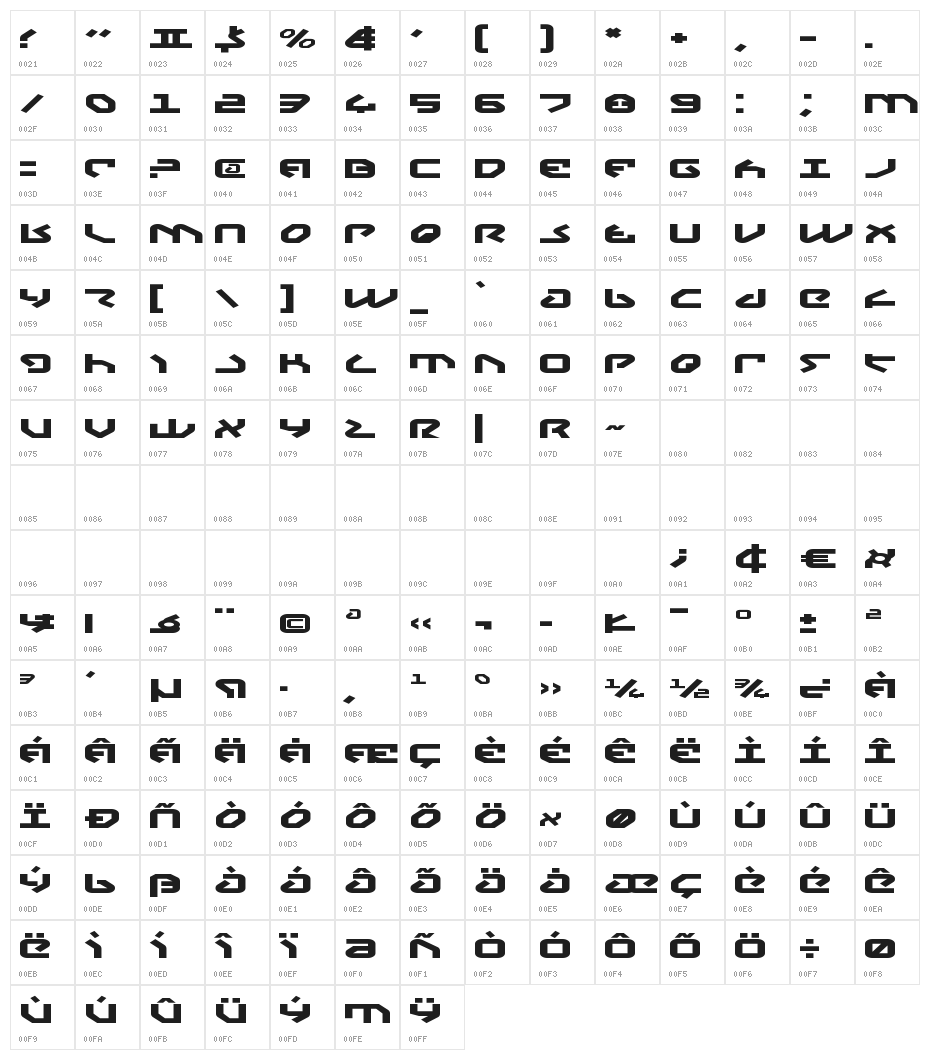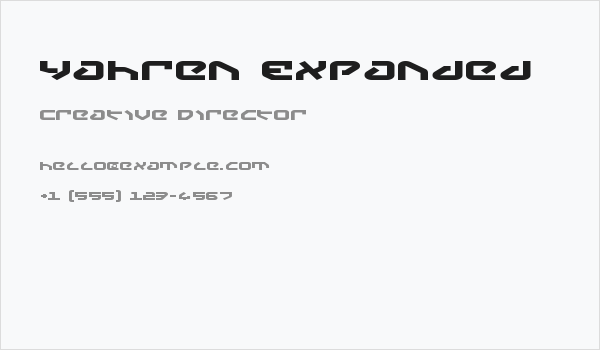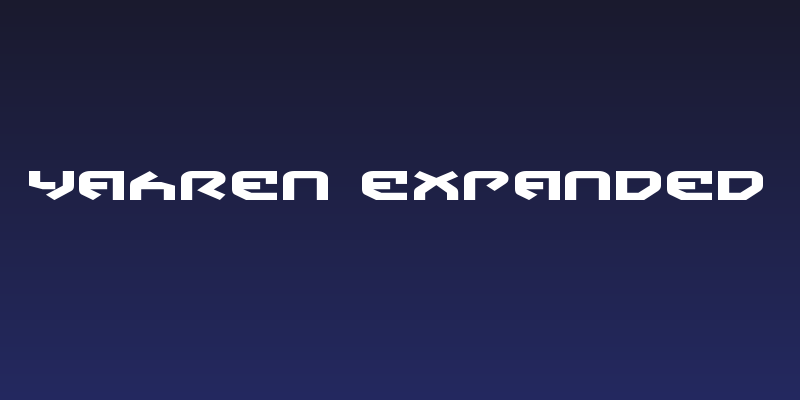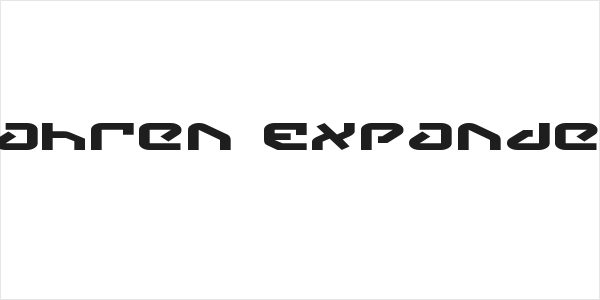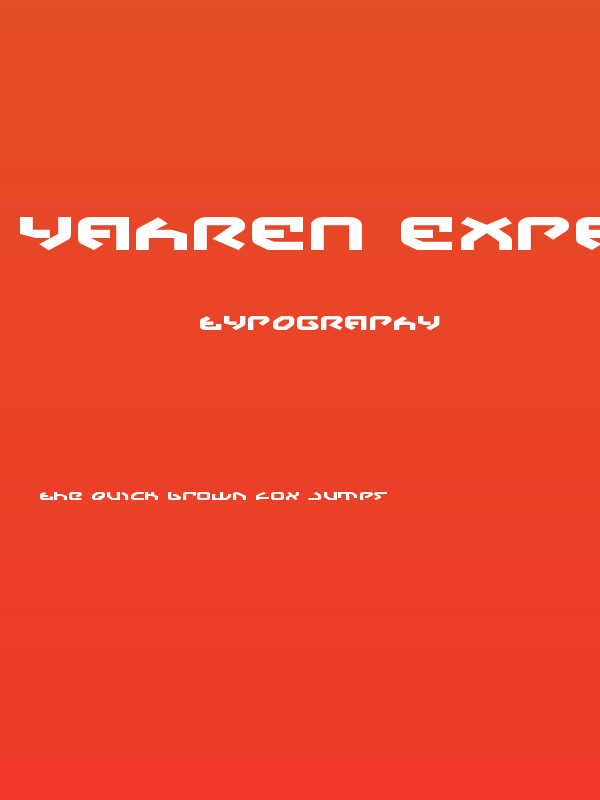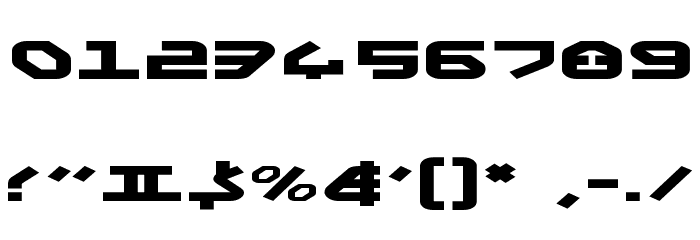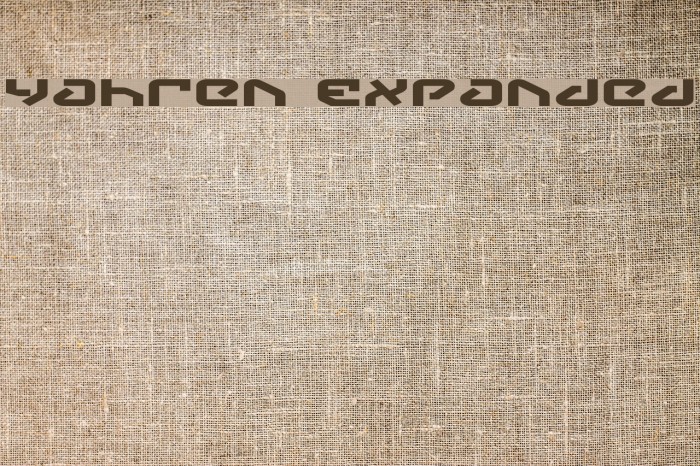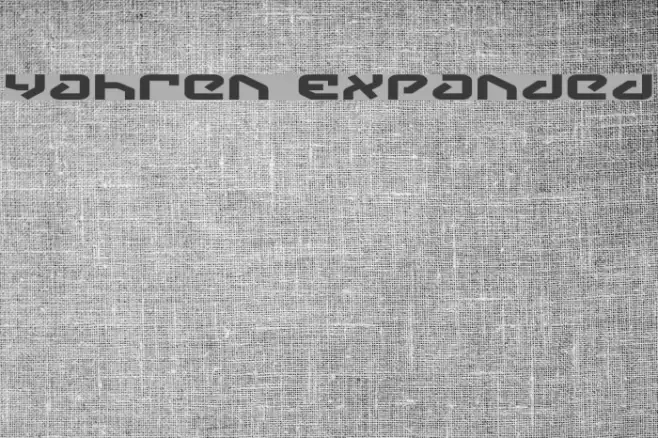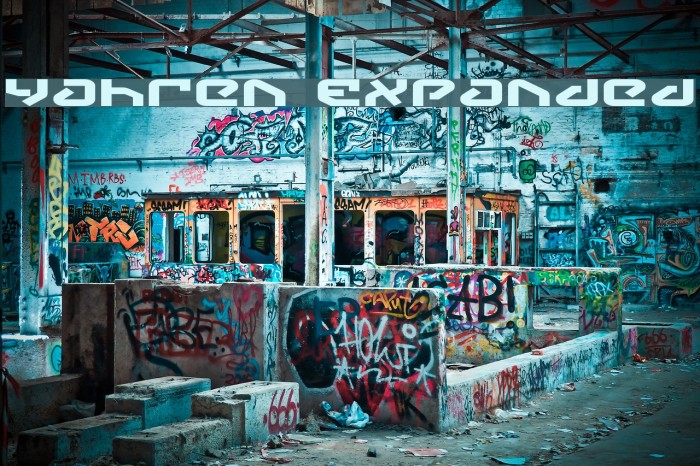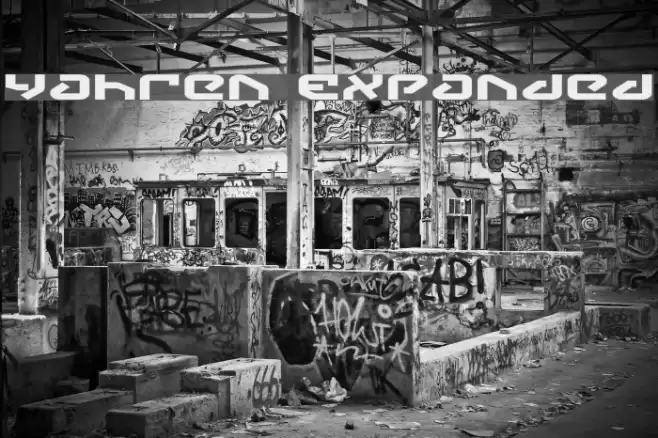
Yahren Expanded Font
✎ Futuristic
| 分类 | Futuristic |
| 宽度 | Expanded |
| 整体风格 | Futuristic |
| 推荐项目 | Ideal for sci-fi themed projects, video game titles, tech branding, and futuristic posters. |